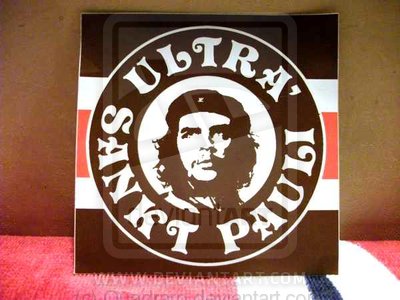
Font Gesucht (mir bekannt durch Ultra' Sankt Pauli)
Es handelt sich um die Victorian von Colin Brignall und Freda Sack (1976) oder einen Klon davon, zB Pretoria. Storybook ist nur einer der vielen Klone. Kommerzielle Klone: http://www.identifont.com/similar?38S
Weitere Klone wurden da schon länger mal gepostet: